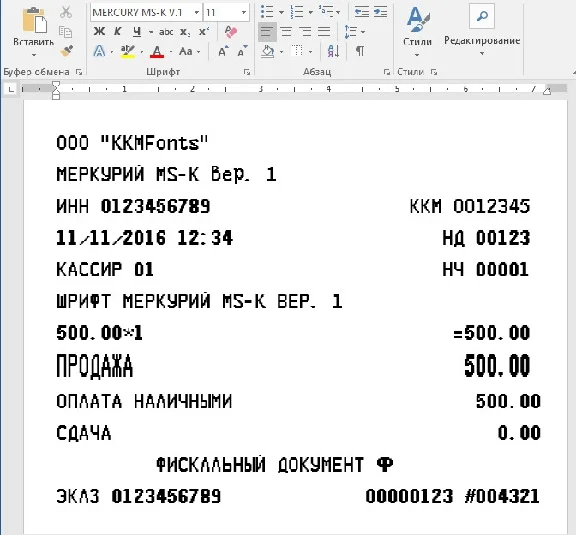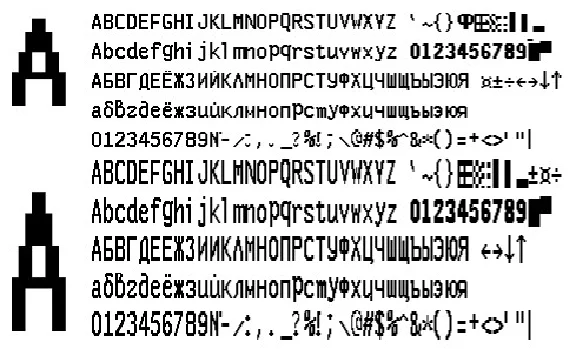
Шрифт ККМ МЕРКУРИЙ MS-К вер. 1(ttf)
Шрифт кассового аппарата МЕРКУРИЙ MS-К версия 1 в формате TTF (русские и английские буквы) для использования в программе Microsoft Word. В архиве находятся стандартный и высокий шрифты в формате TTF и шаблон чека. Вам остается только установить шрифты в систему (обычно C:\WINDOWS\Fonts), открыть шаблон и начать редактирование. Печатать чеки предпочтительно на термопринтере, на кассовой термоленте. Хотя можно печатать и на струйнике и лазерном, с возможностью вывода на факсовую бумагу. Лучшее качество, естественно, при печати на термопринтерах.